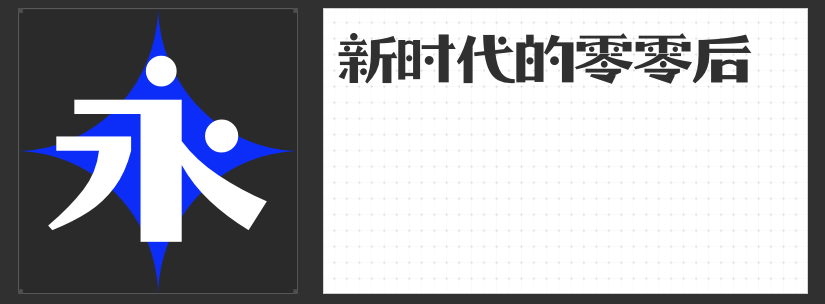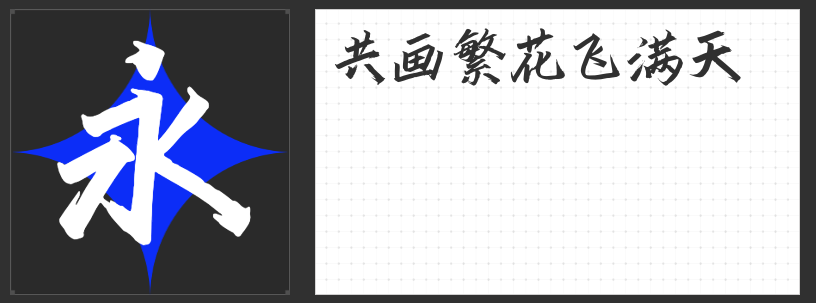
四款高辨识度字体推荐:重塑电商视觉的“语言利器”
在电商视觉竞争白热化的今天,字体不仅是信息载体,更是品牌态度的视觉宣言。本文精选四款风格迥异的商业字体,从传统韵味到现代张力,助您构建差异化的视觉语言体系。
一、造字侠今朝醉简
以酣畅笔墨重构楷书框架,收笔处凌厉的飞白如刀光剑影,中宫紧凑却暗藏舒展余韵。这款字体的独特之处在于“醉而不乱”的平衡感——既保留毛笔书写的自然肌理,又通过数字化处理确保字距行气的规整性。其雄浑劲健的气质,尤其适合需要传递文化底蕴的高端品类,为页面注入东方美学的当代诠释。
二、励字志向黑简 特粗
当圆体的柔和遇上黑体的理性,诞生了这款兼具温度与力量的字体。通过精准控制的外圆角设计,在保持字面充盈感的同时,巧妙化解了传统黑体的机械感。特粗字重确保了移动端显示的清晰度,而笔画末端的轻微弧度处理,则让长文本阅读更显舒适。这种刚柔并济的特性,使其成为科技产品详情页、企业服务类banner的理想选择。
三、励字勇敢黑简 特黑
去繁就简的极简主义设计,将视觉焦点凝聚于纯粹的笔画力量。特黑字重配合均匀的横竖比例,形成如金属浇筑般的视觉压迫感,而撇捺的钝角处理则避免了生硬感,在远距离识别场景中具有绝对优势。这款字体天生适合作为促销头图的核心元素,其醒目特质能有效缩短用户决策路径。
四、字恋狂零零后简繁
突破常规的“错位游戏”设计哲学,将圆形模块与拱形笔画进行解构重组。每个字符都像独立的艺术装置,既保持基本辨识度,又充满随机趣味的视觉惊喜。这种充满实验性的设计语言,精准击中年轻群体的审美偏好,尤其适合潮玩电商、文创品牌的个性化表达需求。
从文化传承到未来想象,这四款字体以不同维度拓展了电商视觉的可能性。当文字突破信息传递的底层功能,进化为品牌与消费者对话的情感媒介,选择合适的字体,便是构建视觉认同的第一步。